Шрифти в CSS. Основи CSS для початківців. урок №6
У цьому уроці я розповім, як в CSS коді можна швидко змінити шрифти сайту, розмір, стиль і т.д.
В кінці я приготував для вас цікавий фокус. Я покажу, як підключити до вашої веб сторінці або сайту нестандартний шрифт. Непоганий бонус, погодьтеся!
Стиль шрифту в CSS
Властивість «FONT-STYLE»
Якщо ви захотіли поміняти стиль шрифту, а саме, зробити текст курсивом або просто похилим, то скористайтеся правилом «font-style».
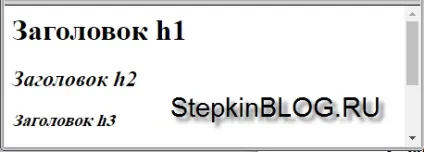
Товщина шрифту в CSS
Властивість «FONT-WEIGHT»
Якщо ви хочете зробити шрифт жирним, використовуйте правило «font-weight».
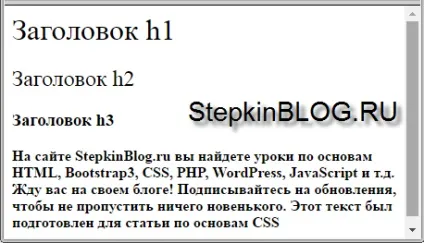
Можна вказати товщину шрифту і звичайними цифрами від 100 до 900.
Розмір шрифту в CSS
Властивість «FONT-SIZE»
Шрифт можна змінювати за розміром. Для цього використовуйте правило «font-size».
Значення задається в «px» і «%».
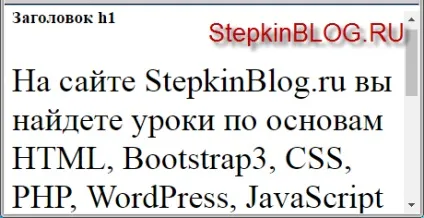
Шрифти в CSS
Властивість «FONT-FAMILY»
На кожному комп'ютері встановлені стандартні шрифти, такі як «Times New Roman», «Arial» або «Verdana». Вибір шрифту залежить від смаку кожного, але потім він впливає на те, як зовні буде виглядати сайт.
Щоб вказати шрифт, скористайтеся правилом «font-family».
Можна ставити в правилах кілька шрифтів. Це на той випадок, якщо у користувача немає першого шрифту, тоді підключиться другий.
Зверніть увагу, шрифт «" Times New Roman "» написаний в лапках ( "").
У лапки беруться ті шрифти, в яких назва складається з двох і більше слів і є прогалина між словами.
сімейство шрифтів
Можна в правило «font-family» прописати і ціле сімейство шрифтів.
Напевно, ви мене не зовсім зрозуміли. Зараз спробую пояснити.
Існує безліч видів шрифтів, які утворюють так звані сімейства.
Існує всього п'ять родин шрифтів:
- sans-serif - шрифти без зарубок (як Arial).
- serif - сімейство шрифтів із зарубками (як Times New Roman).
- monospace - моноширинних шрифти, ширина кожного символу в такому сімействі однакова.
- cursive -курсівние шрифти.
- fantasy - художні та декоративні шрифти.
А можна і ось так:
Підключення нестандартних шрифтів в CSS
Властивість «@ FONT-FACE»
Буває такий момент, що вам просто необхідно встановити на сайт нестандартний шрифт, тобто, шрифт, який не встановлений за замовчуванням у користувача на комп'ютері.
Правило «@ font-face» дозволяє нам імпортувати зовнішній файл шрифтів в документ. Після імпортування, ми можемо використовувати нестандартний шрифт як звичайний через правило «font-family».
Залийте будь-який нестандартний шрифт формату «ttf» в папку вашого сайту поруч з файлом css, це для того, щоб ви не заплуталися і правильно написали шлях до шрифту. Для прикладу я візьму нестандартний шрифт з ім'ям «DS-UncialFunnyHand-Medium.ttf».
Ось приклад підключення нестандартного шрифту.
- font-family :. ; - тут пишемо ім'я шрифту;
- src: url (.); - тут вказуємо шлях до файлу зі шрифтом який буде завантажуватися з сайту.
Ось повний приклад з підключенням нестандартного шрифту і його використання.